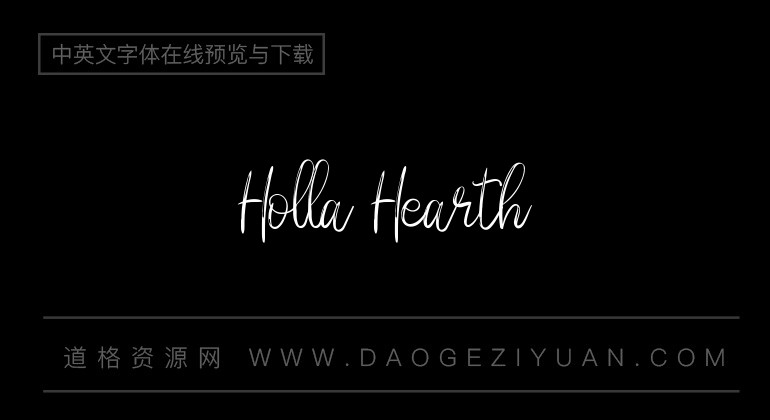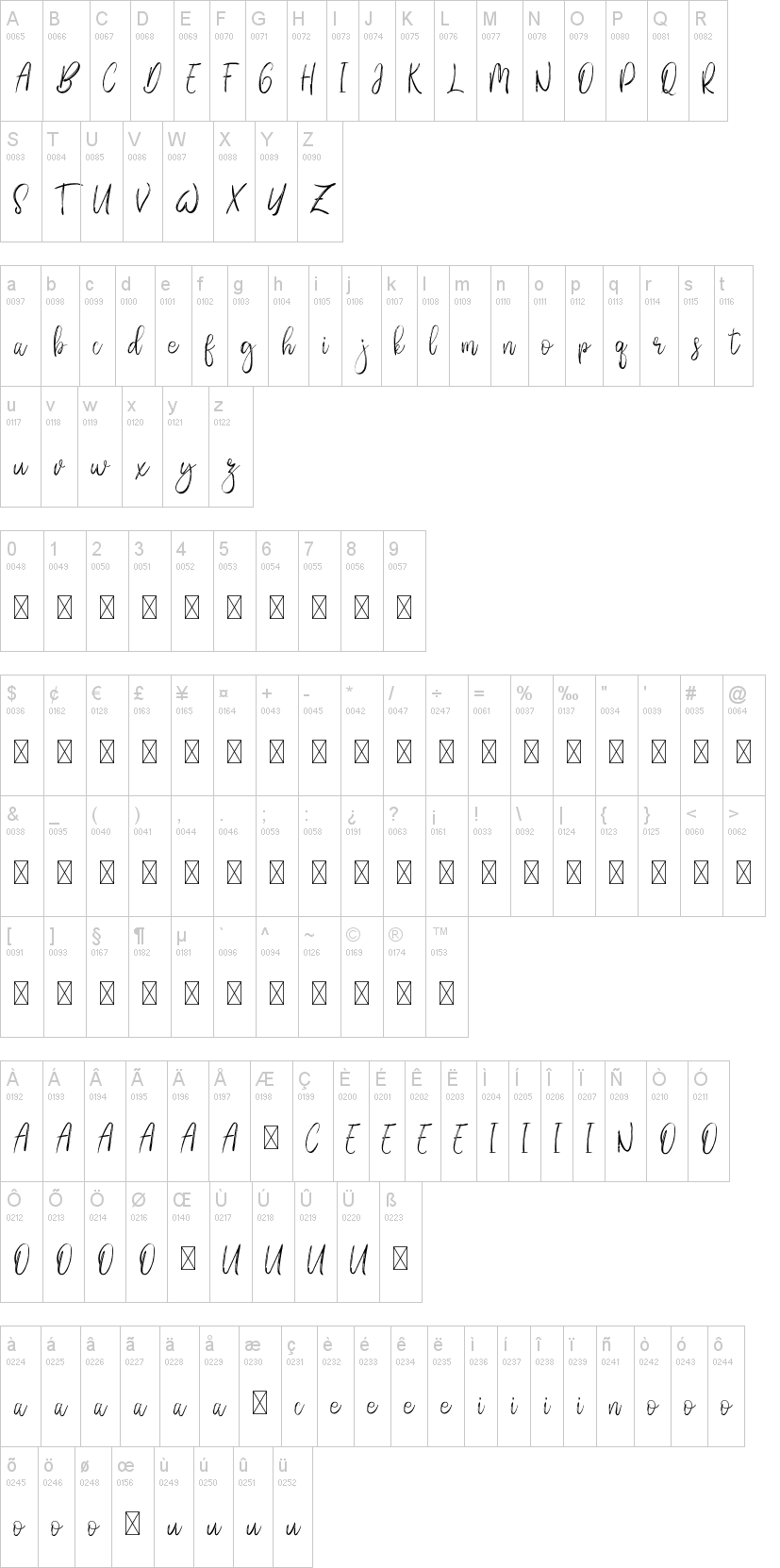
Holla Hearth 字体是一款拥有现代风格的字体,它具有优雅、精致和现代的特点,可以适用于各种应用程序,如标志、标题、广告、品牌标识等。它的字体曲线精致,细节丰富,画面十分清晰,能够让您的设计更加出色。此外,它也支持多种语言,可以满足不同文化背景的需求。内容介绍
Holla Hearth是一款非常不错的手写艺术字体,具有很好的视觉感,适合于文化类的宣传设计、商业类品牌的广告和产品包装设计以及个性化文字排版等较多场景。